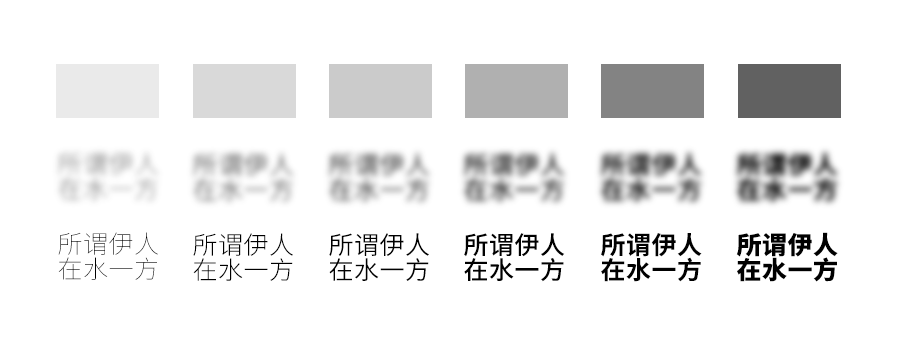
“灰度”指的是阅读字句或整篇文章时,视觉上感受到每个字的相对浓淡程度。字体的“灰度”是指字体在不同亮度、字号、距离下的显示效果。
△ 模拟灰度感受
由于汉字笔画数量差异大,设计字型时需考虑排版呈现,通过调整每个字的浓淡程度来增加易读性。
△字体字重的灰度,对视觉的影响
优化字体的灰度可以显著提升在不同设备和应用场景下的识别性和阅读体验。例如,在不同设备的应用场景下,字体的灰度会影响在弱光环境、小字号、远距离下的识别性。因此,优化字体的灰度,让新字体在不同场景下具有更好的识别性和阅读体验。
灰度的修正需依赖设计师的经验进行主副笔粗细分配及骨架微调,并非单纯计算字面所占的黑色面积。
△笔画数量较多的需要调整粗细,以达到视觉上灰度的相同